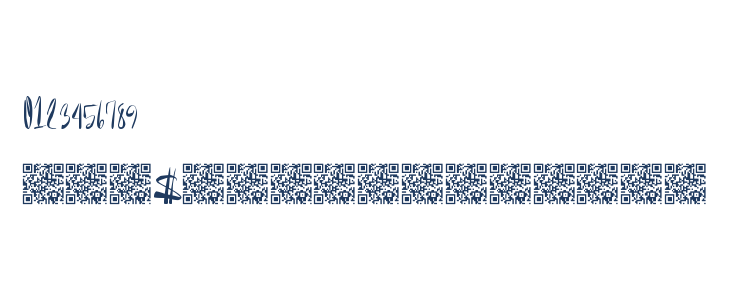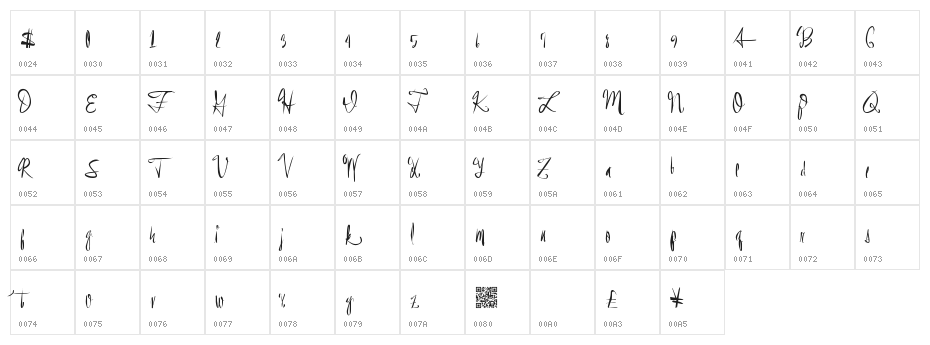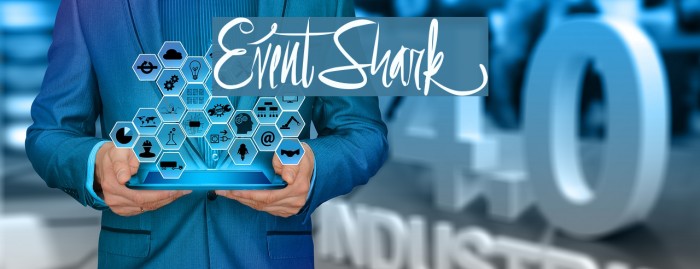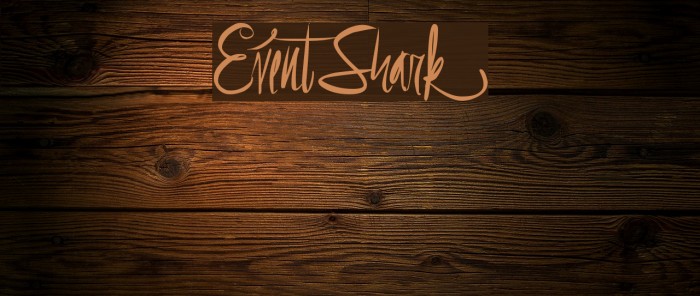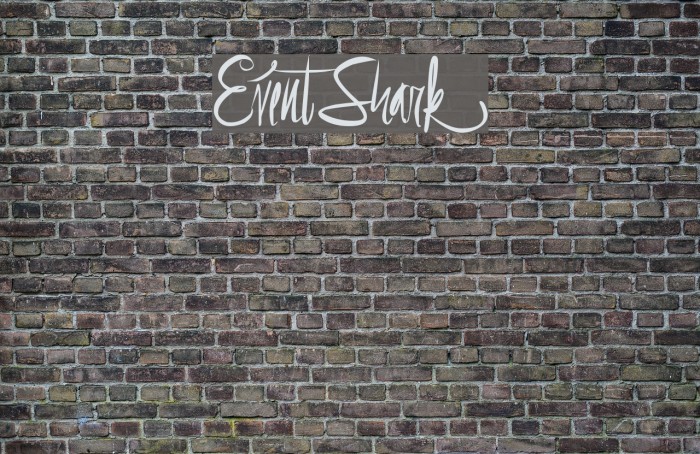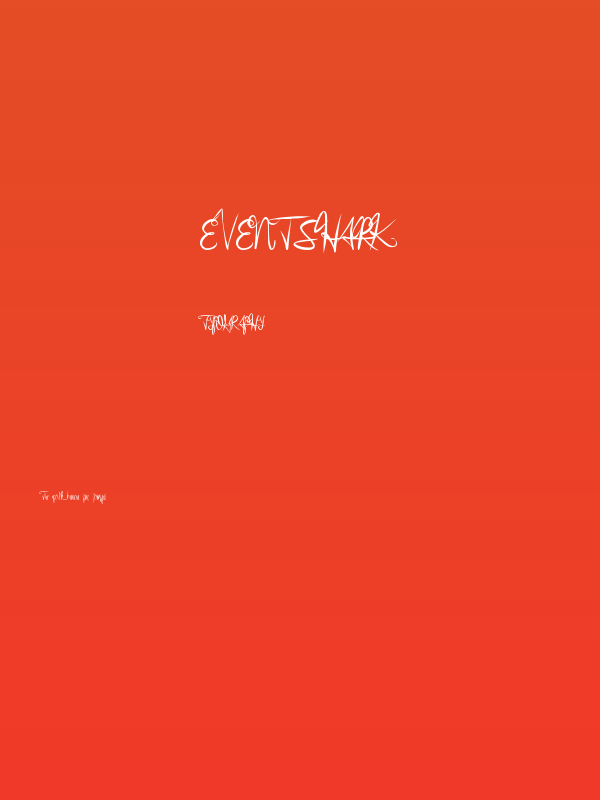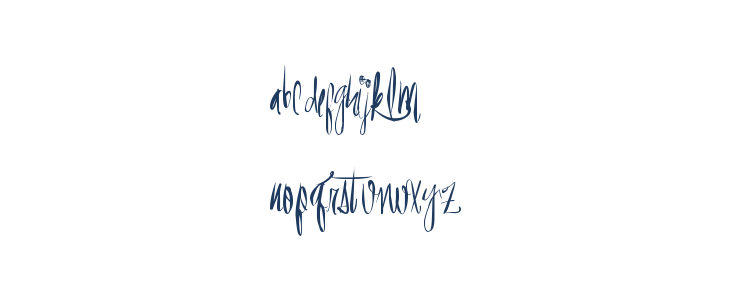
EventShark Font
✎ Handwritten
| 使用场景 | Logos, Invitations, Artistic Posters |
| 推荐项目 | Ideal for wedding invitations, artistic posters, branding for luxury products, and any project that requires a sophisticated and creative touch. |